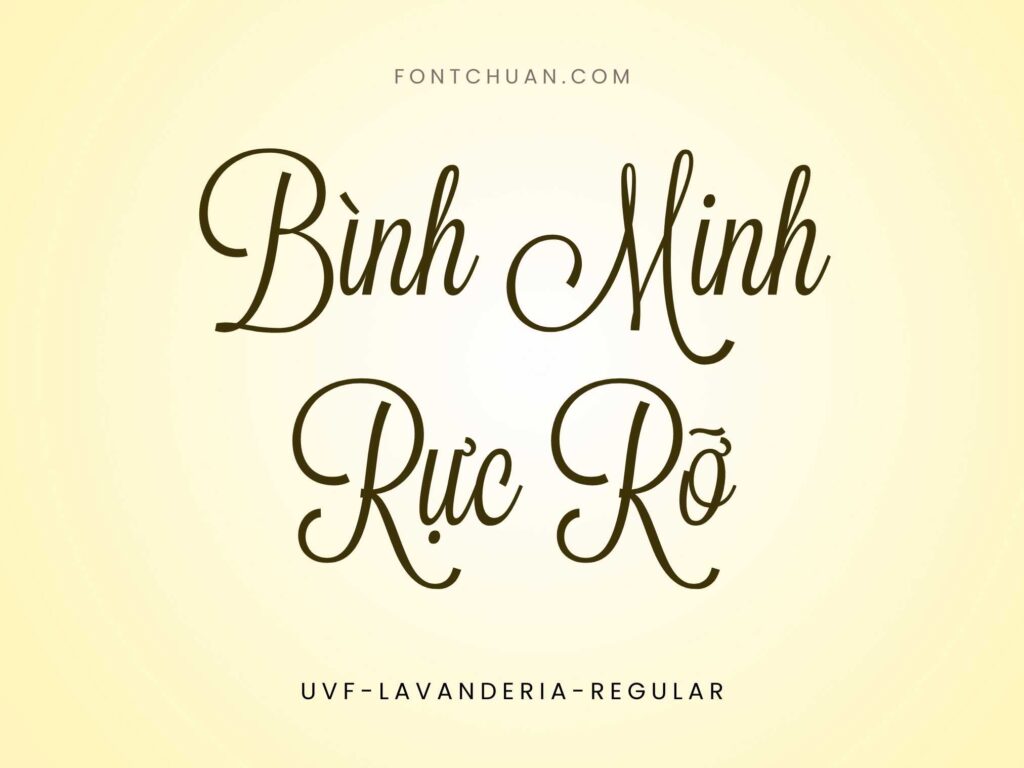
Font UVF Lavanderia Việt Hóa
Lavanderia là một font chữ viết tay được thiết kế bởi James T. Edmondson, lấy cảm hứng từ các bảng hiệu tiệm giặt là ở khu Mission, San Francisco. Với ba phong cách chính: Delicate, Regular và Sturdy, Lavanderia mang đến sự linh hoạt cho các thiết kế cần sự mềm mại và thanh lịch. Font này hỗ trợ nhiều ngôn ngữ nhờ vào bộ ký tự phong phú và các tính năng OpenType.
Với thiết kế uyển chuyển và tinh tế, Lavanderia phù hợp cho các ứng dụng như thiệp cưới, tiêu đề sách, thiết kế logo và các ấn phẩm nghệ thuật. Trong lĩnh vực sự kiện, font này có thể được sử dụng trong các dịp như lễ hội, lễ cưới và các sự kiện văn hóa. Ngoài ra, Lavanderia cũng thích hợp cho các ngành nghề như thiết kế đồ họa, nghệ thuật trang trí, xuất bản, và giáo dục. Nhờ các nét chữ mềm mại, thanh lịch nhưng dễ đọc, Lavanderia có thể được ứng dụng như một Font chữ giáo dục cho các tài liệu học tập, sách giáo khoa, bài giảng hoặc các ấn phẩm giáo dục sáng tạo, giúp truyền tải thông tin một cách trực quan và gần gũi với người học.
Bên cạnh các ứng dụng thanh lịch và nghệ thuật, Lavanderia còn là một font valentine lý tưởng để thiết kế các sản phẩm lãng mạn và tinh tế, như thiệp Valentine, banner hay poster dịp lễ tình nhân. Với các đường nét uyển chuyển, mềm mại và tinh tế, font này giúp các thiết kế vừa thanh lịch, vừa ấm áp và ngọt ngào, tạo cảm giác gần gũi, phù hợp cho các dự án sáng tạo mang chủ đề tình yêu và các dịp đặc biệt.